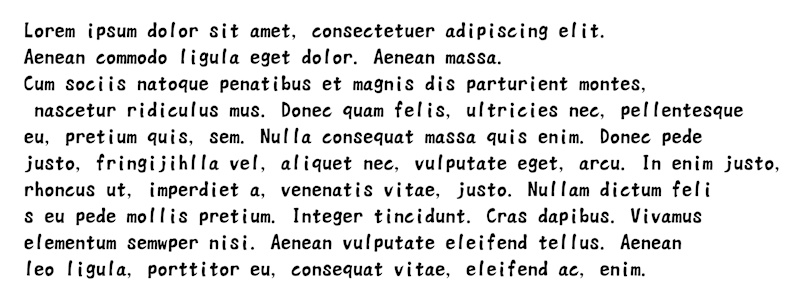
g_いろりフォント(太手書き丸) かな(無料版)
2016/11/24、「g_いろりフォント」に改名しました。旧名「g_太手書き丸」フォントです。収録文字数は変更ありません。 ---- 2016/04/24 「標準」「斜体」「太字」を表示できるよう漢字を追加しました。 ---- コミックのセリフ、描き文字やロゴ等に使用する事を目的として作成したttfフォントです。 このページで配布しているのはプレビュー版(無料版)ver.0.04です。 現在の収録文字は、半角英数字・全角ひらがな・全角カタカナ および、若干の記号・漢字 となっています。 漢字はまだほとんどつくってないので、ほぼ、かなフォントであるとお考えください。日本語文章をがっつり入力したい方は、他のフォントと混植する必要があります。 縦書き対応です。 ■フォント使用の許諾の範囲について 一部の文字を画像化して使用する、 一部の文字を印刷物に利用するなど、 フォントとして再利用できない形での使用は、 デジタル・アナログ、商用・非商用を問わず、だいたいOKです。 加工・変形して使うのもOKです。 ただし、以下の行為については禁止いたします。 ・フォントファイルの再配布・譲渡の禁止 ・フォント自体を利用して利益を得る行為の禁止 ・排外的な権利を主張するのは禁止 ・フォントの作者を騙ること フォント使用の許諾の範囲の詳細については、こちらのページでご確認ください。 →http://font.animehack.jp/#rule